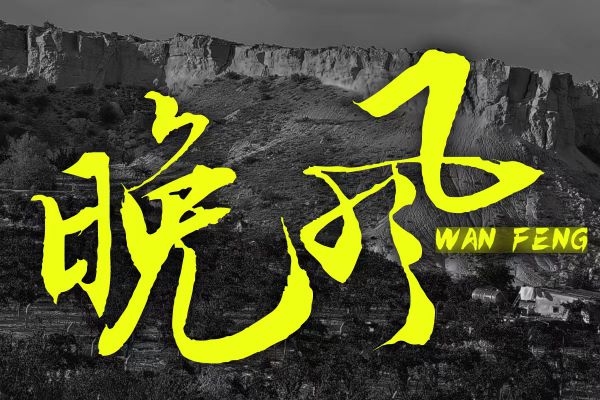
汉仪黄科行书 W
### 汉仪黄科行书 W:挥洒自如的手写体行书典范 汉仪黄科行书 W 是由当代青年书法家黄科历时半年精心打造的手写体行书字体,融合中国风的豪迈气势与手写书法的灵动韵味。字体字形修长,重心偏高,中宫宽博,既展现出行书的飘逸感,又不失结构的稳重。笔画设计独具匠心,尖锋起笔锐利果敢,收笔处融入行书特有的牵丝连带,部分连笔处理更强化了书写的连贯性与节奏感,斜切笔画则为字体注入利落力量感。 汉仪黄科行书 W 兼具俊秀与豪放气质,锐利中暗藏柔美细节,逐字放大后可见丰富的笔触变化,局部放大更具装饰性,尤其适合纵向排列或打散交替排版,在广告海报、产品包装等场景中能营造强烈视觉冲击力。作为汉仪字库旗下特色手写体,推荐与汉仪黄科榜书搭配使用,形成「和而不同」的设计层次,是追求中国风与手写力量感的理想选择,支持简体/繁体中文常规字符集,授权方式为企业专享单独授权。